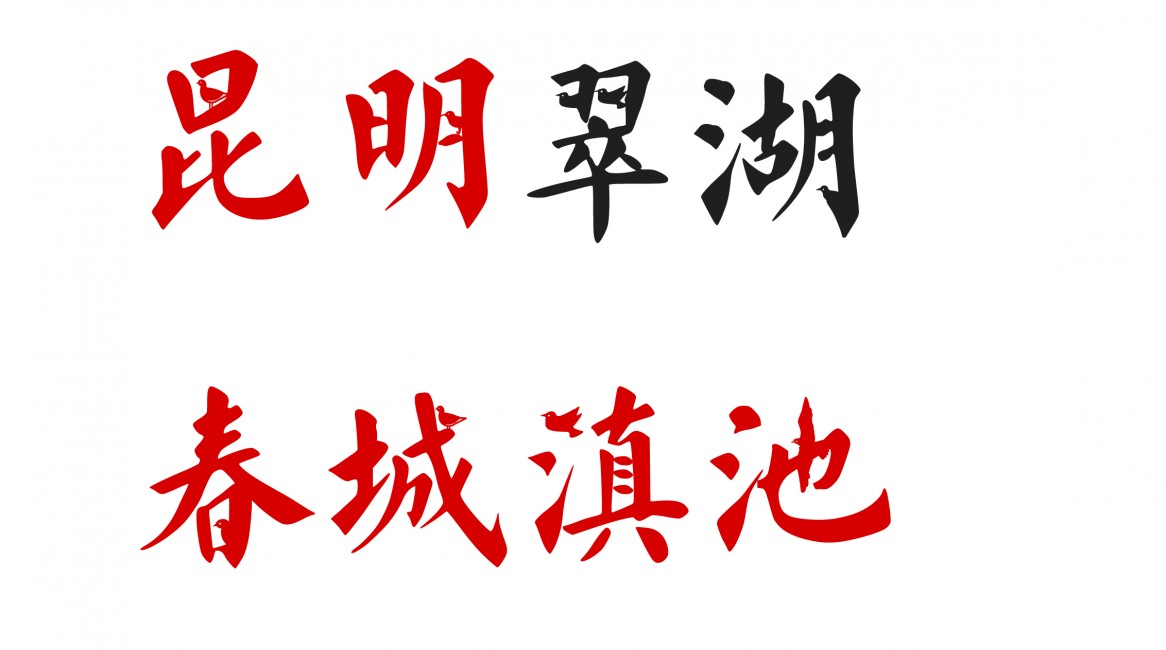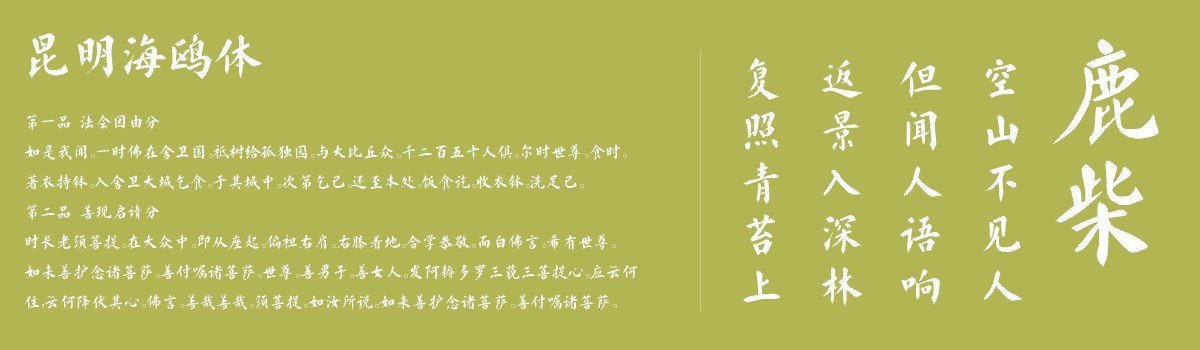
1月2日,“昆明海鸥体”首发暨文化交流合作签约仪式在昆明老街举行。“昆明海鸥体”创作者、字体家AI神笔造字负责人、著名书法家叶根友为昆明送上专属的新年文化礼物——全国首款城市定制型海鸥主题字体。这款被命名为“昆明海鸥体”的字体,全套共6763个汉字,即日起可供全国设计工作者免费使用。
历时2个月打造共6763个汉字
为了讲述昆明人鸥和谐40年感人故事,叶根友经过两个月不断创作,用书法家笔锋+AI造字打造出包含有6763个汉字的“昆明海鸥体”。
叶根友介绍,昆明海鸥体先后经历了六版的更新升级。“我们观察了红嘴鸥起飞、降落、飞翔、觅食等的形态,并将这些形态记录下来,再一次次和汉字笔画融合。”
活动上,叶根友与昆明市文化和旅游局签订了“昆明海鸥体”版权转让协议,把这份专属的新年文化礼物——全国首款城市定制型海鸥主题字体赠送给了昆明市。他还现场书写了今年观鸥季的主题“鸥遇昆明 诗意春城”,赠送给昆明市融媒体中心。
昆明市文化和旅游局副局长王明瑶表示,叶根友独具匠心的创作,为昆明这座城市增添了一份独特的文化魅力。从1985年开始,每年冬季,大批红嘴鸥不远万里飞抵昆明,“人鸥同乐”的画面早已成为昆明的冬日风景线和城市名片。2025年刚好是“人鸥结缘40载”,叶根友创作的“昆明海鸥体”,将海鸥元素融入书法中,既展现了书法的神韵之美,又彰显了昆明的观鸥风情,为昆明观鸥季赋予了独特的文化内涵。今后,通过“昆明海鸥体”的发布和推广,能够吸引更多的游客前来感受春城的魅力,体验“有一种叫云南的生活”。
1月 3日,“昆明海鸥体”发布的相关新闻成为微博、抖音当日热搜,全国重要30多家媒体转载“昆明海鸥体”相关报道。字体的发布引起了广泛关注。
这款被命名为“昆明海鸥体”的字体全套共6763个汉字,即日起供全国设计工作者免费使用。1月3日在字体家等网站“昆明海鸥体”下载量超过1000次。这款字体不仅免费提供给全球用户使用、支持商用。
“昆明海鸥体”文创独宠外地游客
2014年,有中国梦“写梦人”之称的叶根友创作的刀锋黑草书法字体被中共中央宣传部、中央文明办等单位选为中国梦的“梦”字指定书法字体。2024年11月,叶根友看到红嘴鸥飞临昆明后,便开始创作昆明海鸥体。
“我听说过很多昆明人鸥和谐的故事,每年数以万计的红嘴鸥抵达春城后和昆明人共同创造了无数个美妙的瞬间。这是其他城市没有的旅游资源,独属昆明的美景。”叶根友说。
将海鸥的姿态和汉字融合,并不是一件易事。“每一个字不仅要有海鸥的灵动,也要有汉字本身的美感。“我们努力地创作,就想让昆明本地人一眼看出,有只红嘴鸥‘落’在了汉字上。让外地人通过字体来了解人鸥和谐相处40年的故事。”叶根友说。
让昆明海鸥体的设计风格现代且富有动感,笔画中融入了海鸥翅膀的曲线,体现出飞翔的轻盈感。字体的结构设计注重流畅性和美感,细节上则通过曲线和转折展现海鸥的灵动。这种设计不仅增强了字体的视觉吸引力,还赋予其独特的艺术价值。
叶根友及其团队又通过海量的模拟找到最合适和海鸥形态相结合的汉字笔画。通过两个月的不断尝试,让昆明海鸥体字体隽秀且不失稳重典雅,有碑帖中的古碑神韵,也有现代书风的气息,不仅符合现代人简约时尚的审美理念,作为全国首款融入红嘴鸥元素的字体,生动且有趣。
“昆明海鸥体”的“昆明”两字中的都有红嘴鸥的形象,特别是“昆”字中的红嘴鸥形象,设计团队先后做了10多种造型,最后才选定一只站立红嘴鸥的形象。除了昆明两字中有海鸥形象之外,“滇池”“春城”“翠湖”“平安”“美满”等汉字的笔画中都有红嘴鸥的各种姿态。